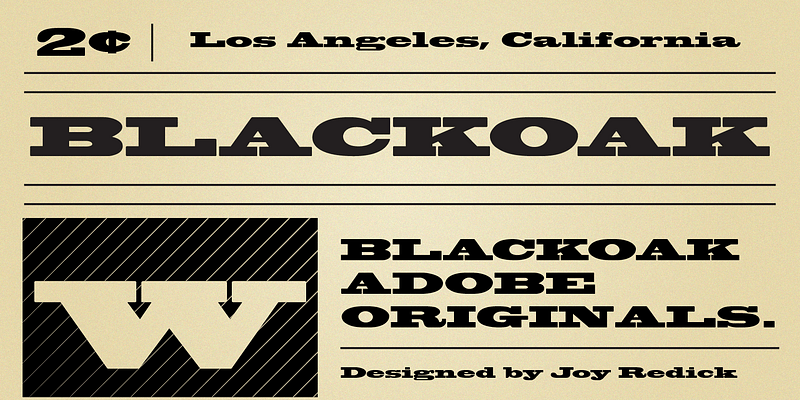
Blackoak es un tipo de letra de Adobe Originals diseñado en 1990 por Joy Redick. Blackoak, adaptada a partir de pruebas de tipos de madera de la colección de la Smithsonian Institution, tiene serifas en forma de láminas y formas de letra extremadamente anchas. Si se utiliza con moderación, Blackoak es una tipografía para cartelería muy llamativa.
El programa Adobe Originals se inició en 1989 como tipográfica interna de Adobe, creado para desarrollar tipos de letra originales con una calidad de diseño ejemplar, fidelidad técnica y longevidad estética.
En la actualidad, la misión del equipo de Type es crear tipos de letra sofisticados e incluso experimentales que exploren las posibilidades del diseño y la tecnología. Los tipos de letra que se publican como originales de Adobe son el resultado de años de trabajo y estudio, y se consideran estándares del sector por la ambición y la calidad de su desarrollo.